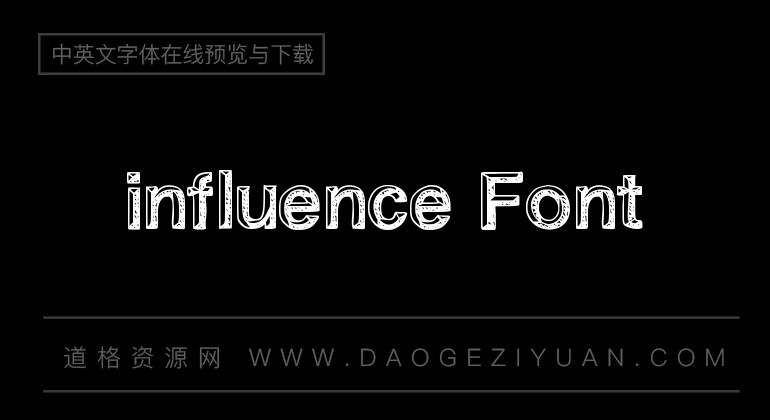
Influence Font 是一种现代化的无衬线字体,其设计风格具有艺术性和创意性。该字体采用了大胆的线条和圆润的曲线,使其看起来非常独特和醒目。Influence Font 支持多种语言和字符集,适用于各种设计项目,例如:广告、标志、海报、包装设计等等。如果您需要一种具有现代感和个性化的字体来提升您的设计,那么 Influence Font 可能是一个不错的选择。内容介绍
influence Font是一款非常不错的手写艺术字体,具有很好的视觉感,适合于文化类的宣传设计、商业类品牌的广告和产品包装设计以及个性化文字排版等较多场景。